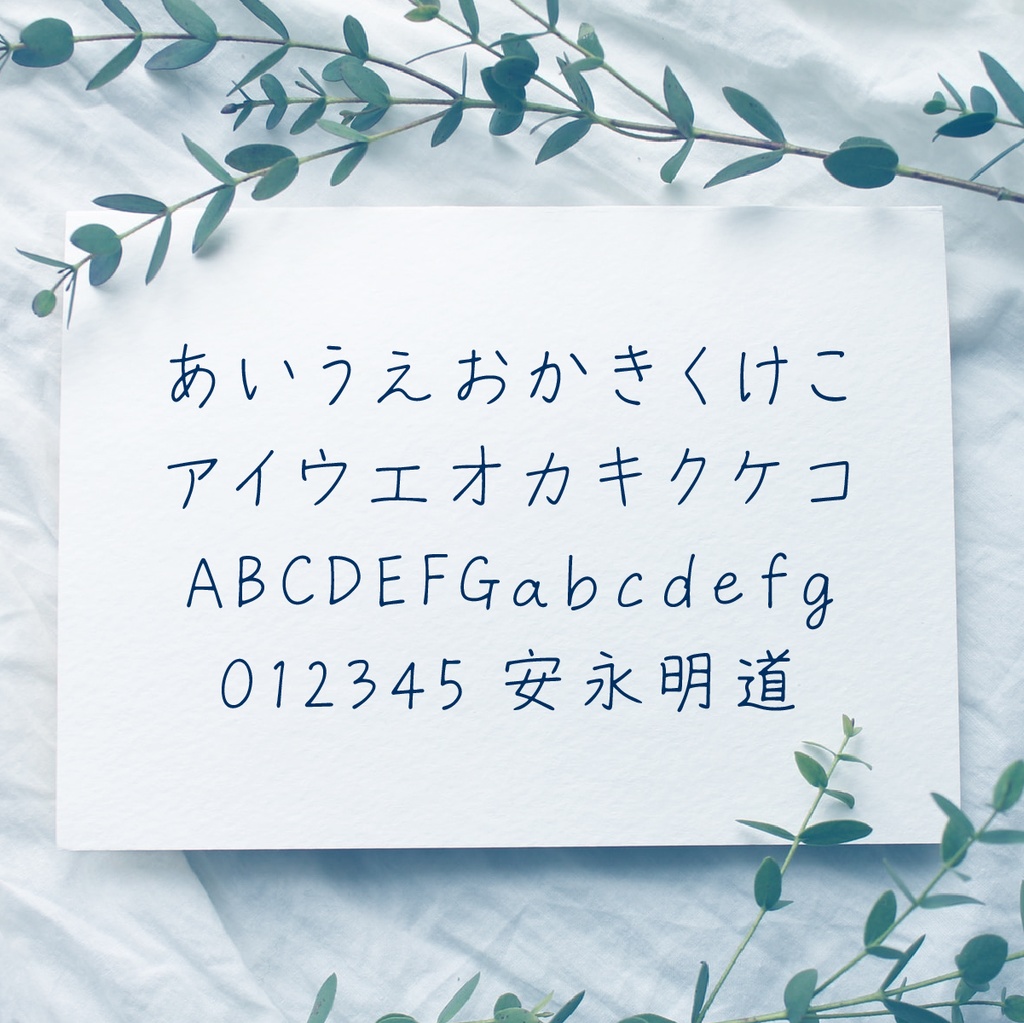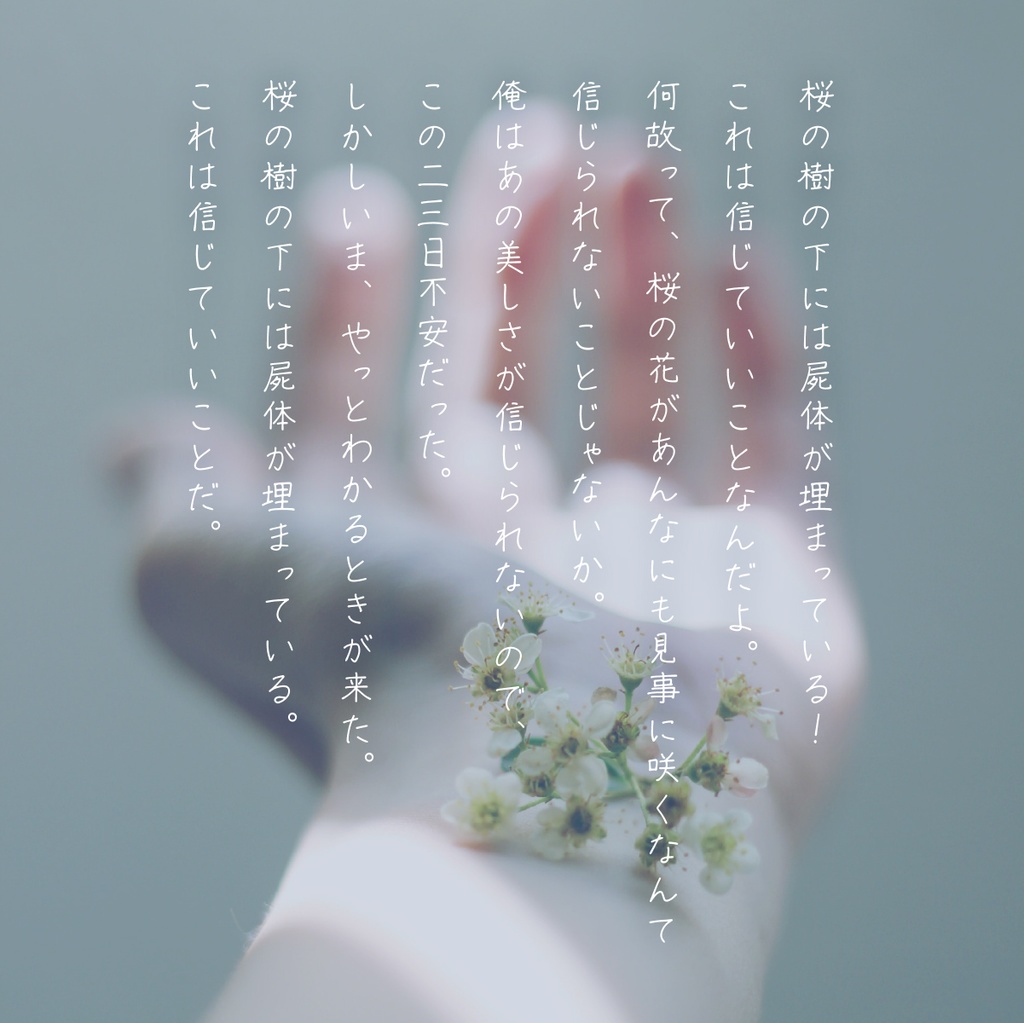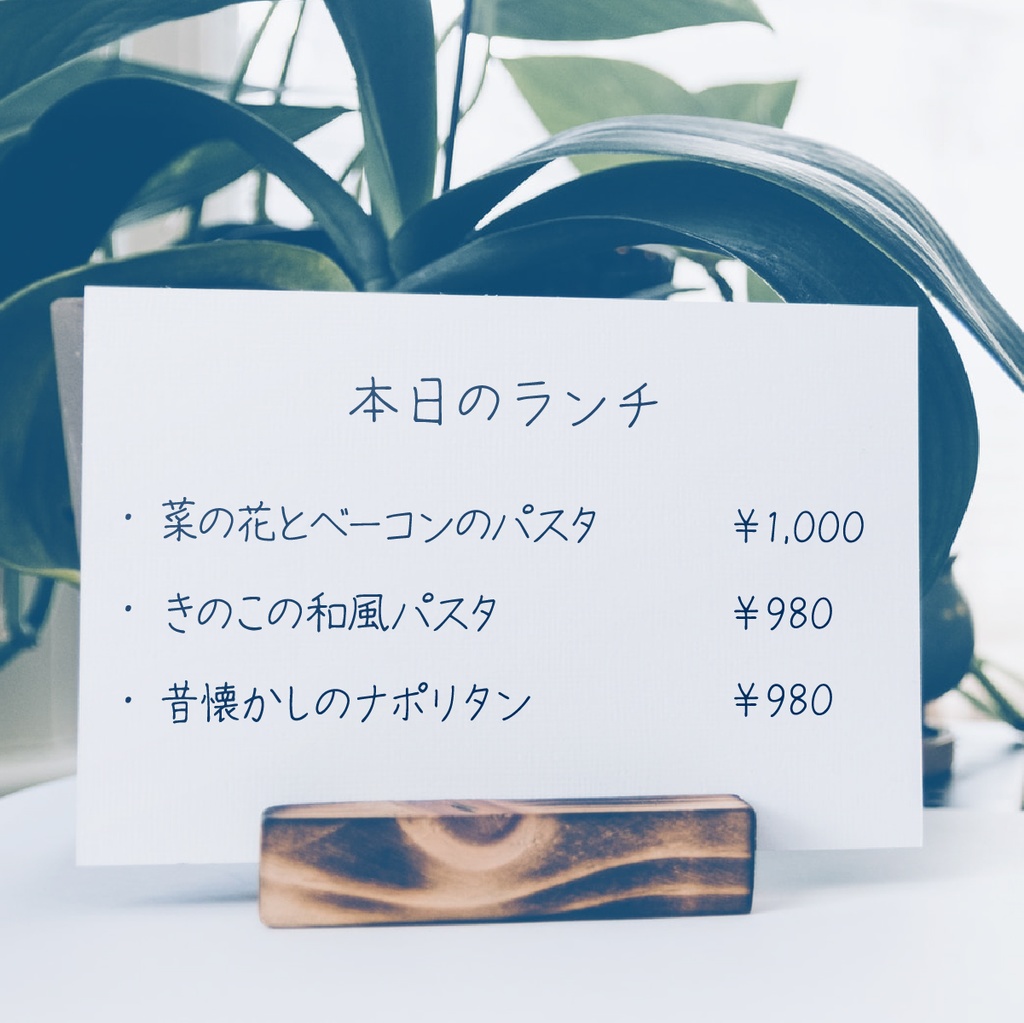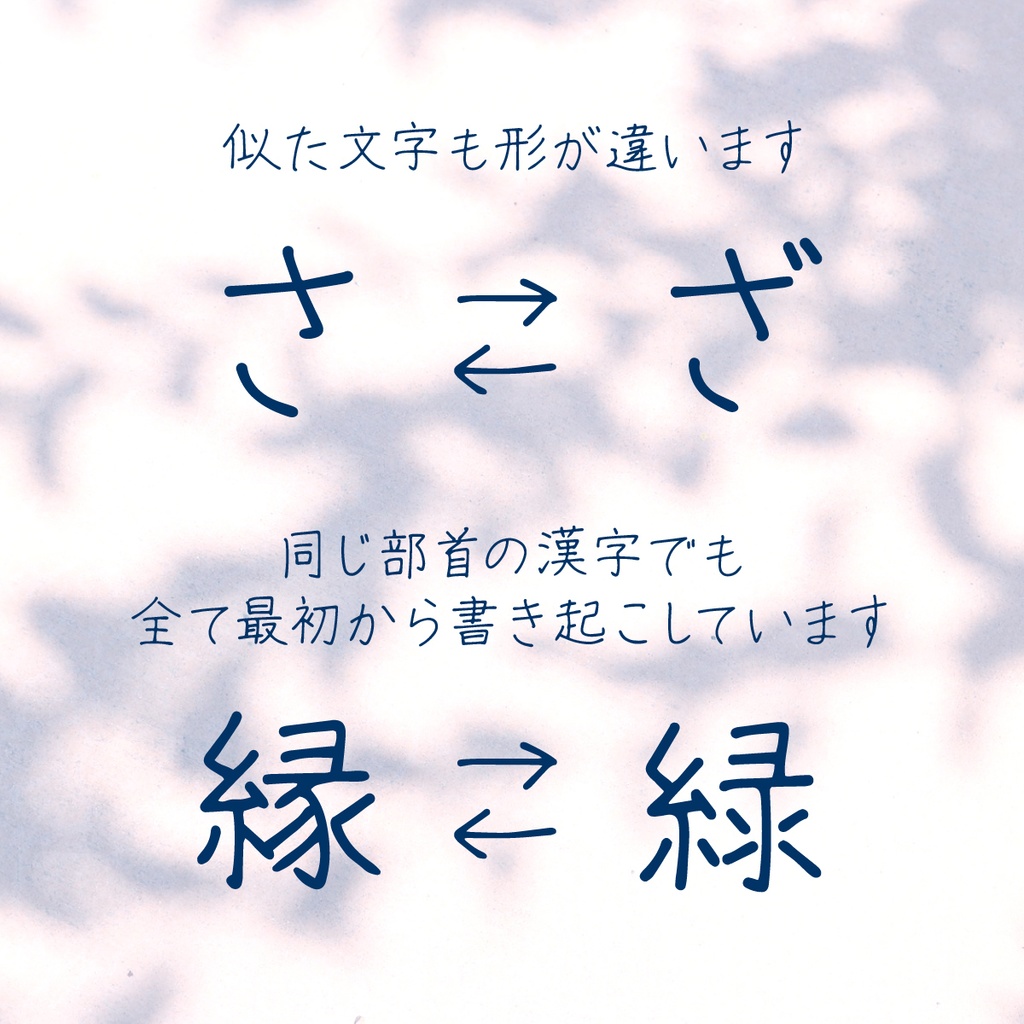
手書きフォント「左利きの彼女」通常版
左利きの作者が丁寧に書いた手書き文字をOpenTypeフォント化しました。
どんなフォント?
ひらがな、カタカナ、英数字、JIS第一規格の漢字、常用漢字、人名漢字の約2950文字+よく使いそうな漢字を約600字収録されているのである程度の文章は打てます。 「薔薇」や「躊躇」「ゔ」「髙」なども打てますよ。 また商用にもお使いいただけます。 手書きの味を出すため全ての文字を手書きしました。 似ている文字、例えば「さ」と「ざ」や「縁」と「緑」などもそれぞれ書いているので、同じ部首を使った漢字でも形が違います。 通常版は今後よく使いそうな漢字は追加していく予定で、 購入していただいた方は無償でアップデート可能にします。 また誤字などありましたら教えてください。 (ハネの有無などは字によって違うものもあります。手書きフォントの味として受け取ってもらえると幸いです。)